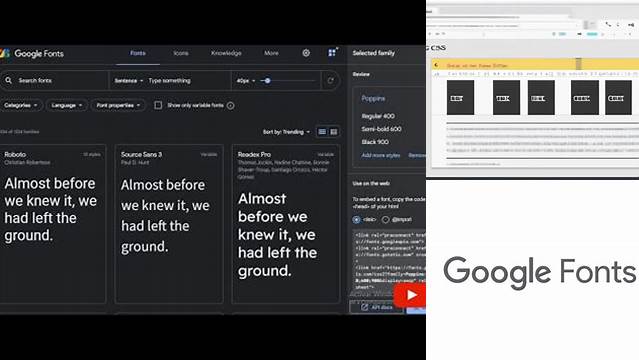
Cómo Usar Google Fonts En HTML: Guía Para Principiantes
Introducción a Google Fonts: Tu Camino Hacia una Tipografía Web Atractiva
¡Hola, amigos! ¿Listos para darle un cambio de imagen a sus sitios web? Hoy vamos a sumergirnos en el fascinante mundo de las Google Fonts, una herramienta gratuita y sencilla para mejorar la apariencia de tus páginas con tipografías atractivas y profesionales. Imaginen esto: ya no más esas aburridas fuentes predeterminadas. Con Google Fonts, tienes a tu disposición una biblioteca enorme de fuentes para elegir, todas diseñadas para la web y fáciles de implementar. Y lo mejor de todo, ¡es gratis! En esta guía completa, te mostraré paso a paso cómo integrar Google Fonts en tus proyectos HTML, desde los conceptos básicos hasta algunas técnicas más avanzadas. Prepárense para transformar la estética de sus sitios web y hacer que la lectura sea una experiencia visualmente agradable. Vamos a ello.
¿Qué Son las Google Fonts y Por Qué Deberías Usarlas?
Google Fonts es una biblioteca de tipografías de código abierto ofrecida por Google. Contiene cientos de fuentes, desde las clásicas hasta las más modernas, diseñadas específicamente para su uso en la web. ¿Por qué deberías usar Google Fonts? La respuesta es simple:
- Variedad: Tienes acceso a una amplia gama de fuentes para elegir, lo que te permite encontrar la que mejor se adapte a la personalidad de tu marca o proyecto. Ya sea que busques una fuente elegante y sofisticada, o algo más amigable y legible, Google Fonts lo tiene.
- Facilidad de Uso: La implementación es increíblemente sencilla. Con unas pocas líneas de código, puedes integrar cualquier fuente en tu sitio web. ¡No necesitas ser un experto en diseño para hacerlo!
- Rendimiento: Las fuentes de Google Fonts están optimizadas para la web, lo que significa que se cargan rápidamente y no afectan negativamente la velocidad de tu sitio. Esto es crucial para la experiencia del usuario y el SEO.
- Accesibilidad: Google Fonts está diseñado para la accesibilidad. Las fuentes están diseñadas para ser legibles en diferentes dispositivos y tamaños de pantalla, lo que mejora la experiencia de usuario para todos.
Beneficios de Usar Google Fonts
Implementar Google Fonts en tus proyectos web tiene muchos beneficios. En primer lugar, la legibilidad de tu contenido mejorará significativamente. Una fuente bien elegida hace que el texto sea más fácil de leer, lo que aumenta el tiempo que los usuarios pasan en tu sitio. Además, Google Fonts te permite crear una identidad visual más fuerte. La elección de una tipografía única y distintiva refuerza la imagen de tu marca y te diferencia de la competencia. También, las fuentes de Google están optimizadas para la web, lo que significa que se cargan de forma rápida y eficiente. Esto es crucial para la experiencia del usuario y el SEO. Finalmente, Google Fonts es una herramienta gratuita y de fácil acceso. Esto te permite experimentar con diferentes fuentes sin incurrir en costos adicionales.
Integrando Google Fonts en tu Sitio Web: Paso a Paso
¡Manos a la obra, amigos! Aquí te mostraré cómo integrar Google Fonts en tu sitio web en unos simples pasos. Es más fácil de lo que piensas, ¡créeme! Y recuerda, practicar es la clave. Después de leer esta guía, te animo a que juegues con diferentes fuentes y estilos para ver cuál se adapta mejor a tus necesidades.
1. Elige tu Fuente en Google Fonts
Lo primero es lo primero: necesitas elegir la fuente que quieres usar. Ve a la página de Google Fonts (fonts.google.com) y explora la biblioteca. Puedes filtrar por categorías (serif, sans-serif, display, etc.), idiomas y estilos. Una vez que encuentres una fuente que te guste, haz clic en ella.
2. Selecciona los Estilos y Descarga el Código
En la página de la fuente, verás una lista de estilos disponibles (regular, bold, italic, etc.). Selecciona los estilos que necesitas para tu proyecto. Google Fonts te mostrará una vista previa de cómo se verá la fuente en diferentes tamaños y estilos. Después de seleccionar los estilos, haz clic en el botón "View selected families" (o el icono de la bolsa) en la parte superior derecha.
3. Importa la Fuente en tu HTML
Hay dos formas principales de integrar Google Fonts en tu HTML: usando el enlace <link> o usando la directiva @import en tu CSS.
- Usando
<link>: Este es el método más común y recomendado. Copia el código<link>que te proporciona Google Fonts y pégalo en la sección<head>de tu archivo HTML. Este código le dice al navegador dónde encontrar la fuente. - Usando
@import: Si prefieres, puedes usar@importen tu archivo CSS. Copia la directiva@importque te proporciona Google Fonts y pégala al principio de tu archivo CSS.
Ejemplo con <link>:
Ejemplo con @import (en tu archivo CSS):
4. Aplica la Fuente a tu CSS
Ahora que has importado la fuente, es hora de aplicarla a tus elementos HTML. En tu archivo CSS, usa la propiedad font-family para especificar la fuente. Por ejemplo, para aplicar la fuente Roboto a todos los párrafos de tu sitio:
Conclusión: Dale un Toque Personal a tu Web con Google Fonts
¡Enhorabuena, llegamos al final! Espero que esta guía te haya proporcionado todo lo necesario para empezar a usar Google Fonts en tus proyectos web. Recuerda, Google Fonts es una herramienta poderosa que te permite transformar la apariencia de tu sitio web de manera fácil y gratuita. Experimenta con diferentes fuentes, estilos y combinaciones para encontrar la que mejor se adapte a tus necesidades y a la identidad de tu marca. No tengas miedo de experimentar y jugar con las fuentes: la práctica hace al maestro. ¡Anímate a darle a tu sitio web ese toque personal que lo hará destacar! Y recuerda, si tienes alguna pregunta, no dudes en consultar los recursos de Google Fonts o buscar ayuda en línea. ¡Mucha suerte y a crear sitios web increíbles! ¡Hasta la próxima, amigos!